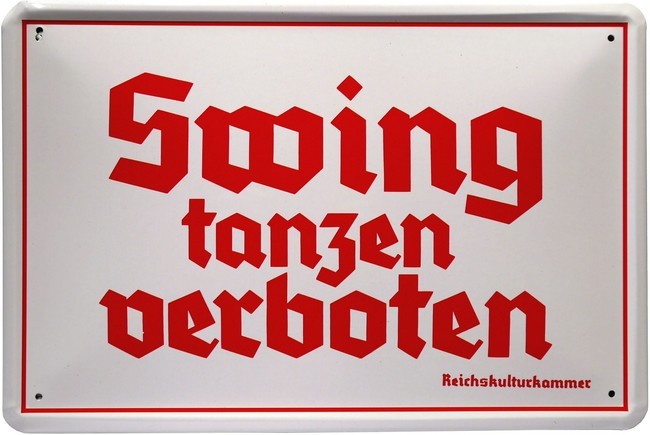
Hallo kann mir jemand verraten wie diese Schriftart heißt?
das ist eine verunglückte Nachahmung der vielen, kaum unterscheidbaren vereinfachten Frakturschriften vom Typ „Schlichte Gotisch“. Der Nachahmer des Schilds kannte selbst keinen richtigen Schriftentwurf, so kommt es zu den üblen Verzerrungen vor allem des ‚e‘, Fraktur schreiben konnte er auch nicht - das große ‚S‘ ist in den Schriften des Dritten Reichs manchmal in der gezeigten Weise von der Antiqua ausgeborgt zu sehen, das kleine ‚s‘ wurde dort aber nie im Wortinneren als End-s ausgeführt.
In die Nähe dieser Plagiatorenschrift kommen die Schriften ‚Tannenberg‘, ‚National‘ und ‚Potsdam‘.
Sieht aus wie eine Abwandlung der Tannenberg-Schriftart.
bei der gezeigten unbeholfenen Verzerrung lässt sich Tannenberg nicht von National und Potsdam unterscheiden.
Hat er wohl auch nicht, denn das wurde m. E. am Computer erzeugt (weil alle gleichen Buchstaben exakt gleich aussehen).
ja, das ist sicherlich am Computer erzeugt - die gruseligen schiefen Linien, wo eigentlich Parallelen hingehören, gibt es nicht, wenn man sowas mit Feder oder Pinsel macht; auch die hässliche Serife am e kann man kaum in dieser Art erzeugen, wenn man von Hand schreibt. Die zu breiten Flächen im Inneren der Buchstaben sind allerdings ein sehr häufiger Fehler, der auch vorkommt, wenn man so eine Schrift „von Hand“ imitiert.
Ein Fehler, der einem am Computer nicht passiert, wenn man Fraktur schreiben kann, ist die Verwendung des End-s im Wortinneren.
Wie auch immer: Es gibt für die genannten Schriften Fonts, mit denen die Buchstaben richtig dargestellt werden.